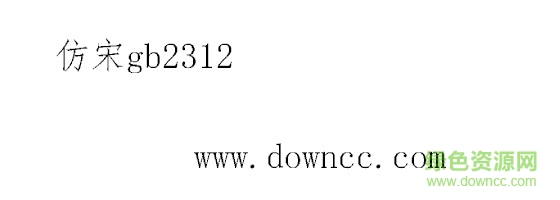
仿宋國(guó)標(biāo)字體就是仿宋gb2312字體,是公文文件常用的字體。不僅可以在全平臺(tái)顯示的,而且也可以更好的辨識(shí)每一字。安裝完成字體之后所有的軟件就可以讀取字體。歡迎下載!
仿宋國(guó)標(biāo)字體是一款電腦上的字體,總的來(lái)說(shuō)屬于仿宋體的分類。字體安裝方便,具有工整、筆畫均勻的特點(diǎn),適用于各類打印、印刷內(nèi)容。
1、仿宋國(guó)標(biāo)字體常用于印刷工作。
2、筆畫粗細(xì)均勻,有長(zhǎng)、方、扁三體。